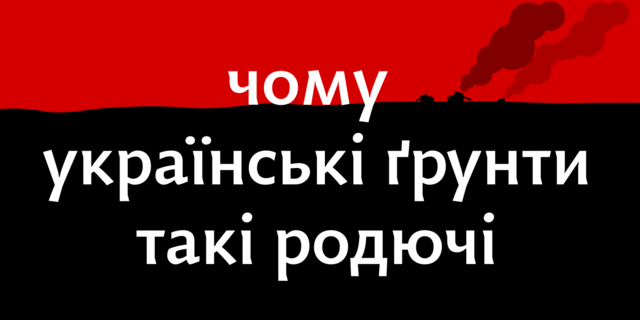
Гуманистический украинский полугротеск универсального назначения. Благодаря гуманистическим пропорциям и несколько каллиграфической остроте шрифт ненавязчиво тревожит глаз, оставаясь одновременно «крепким» современным гротеском. А асимметричные засечки, характерные буквы и альтернативы придают шрифту украинскую окраску. В составе знаков славянская кириллица, европейская латиница и монотоническая гречица. Содержит традиционные и оригинальные лигатуры, варианты цифр, дроби, стилистические и исторические альтернативы. Шрифт разработал Андрей Шевченко в 2007-2022 году.